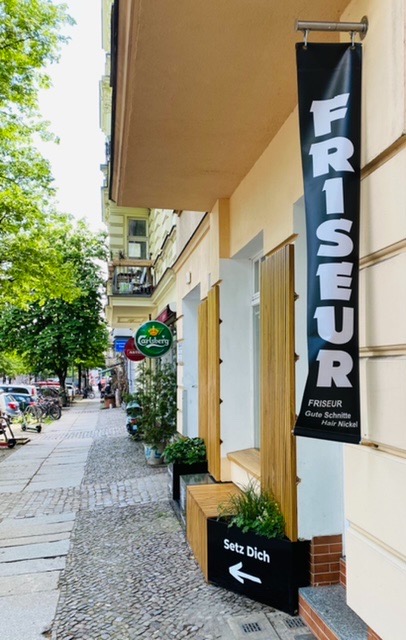
Suche Schrift von »Electric Guitar« aus Tocotronic-Video
Die Schrift ist nicht erhältlich, bitte respektiert unseren Entwurf und baut sie auch nicht nach. Und ich bitte darum, dass falls jemand irgendwie eine Kopie davon haben sollte diese nicht, auch nicht privat, zu verwenden.
Ich bin ein wenig irritiert. Wie kommst du darauf, dass hier jemand eure Schrift nachbauen oder illegal einsetzen könnte?
Und das irgendwo jemand sich in einen Font-Editor einarbeitet, und sich an den Nachbau dieser Schrift heran macht, ohne von deiner Einstellung dazu zu wissen, und diese dann vielleicht auch nur privat nutzt und vielleicht diese dann irgendwann auf eine der Freefont-Seiten auftaucht, wird man auch kaum verhindern können. Wie wissen das jetzt, OK, und es gibt auch noch soo viel, was man machen kann. Wir werden deinen Wunsch also auch respektieren, aber sonstwo?  Zumal die Möglichkeit dagegen vor zu gehen doch eher schwach sind, was jeder Schriftgestalter immer wieder feststellen muss. - siehe auch hier: https://de.wikipedia.org/wiki/Rechtsschutz_von_Schriftzeichen
Zumal der Entwurf ja auf einer vorhandenen Schrift aufbaut und es auch vorher schon sehr ähnliche Schriften gab ...
So sehr ich mich über Dein ursprüngliches Interesse gefreut habe, so sehr wundere ich mich jetzt über Deine Aussage, dass die Schrift ja ohnehin nur eine Variante einer schon vorhandenen sei und doch nicht so besonders. Sind die Trauben jetzt, wo sie sich als nicht greifbar herausgestellt haben, sauer geworden?
Es geht mir bei meiner freundlich formulierten Bitte, den Entwurf zu respektieren nur darum etwaigen Begehrlichkeiten von Leuten, die wie ich "tocotronic schrift" googlen vorzubeugen, und zu bedeuten, dass wir nicht wünschen dass jemand denkt dass wäre ieine anonyme Schrift mit der man herum"forken" könne.
Allgemein hab ich gar nichts gegen Schriftmodifikationen oder Sampling, das kann ja schon eine antimonopolistische Geste der Aneignung sein wenn jemand z.B. das S aus der Disney-Schrift auskoppelt. Und es würde auch einer großen Firma, die seit Jahrzehnten den Schriftentwurf eines vertraglich enteigneten oder längst verstorbenen Designers melkt, nicht weh tun, wenn man mal "ihre" Schrift auf einem Flyer für eine queere Technoparty oder für ein Schulprojekt verwendet.
Hier ist aber es die Hausschrift einer Band, mittlererweile Teil ihrer künstlerischen Identität und ich meine, das ist nicht übertrieben hier zu sagen: freut euch doch über diese kleine Blume in der Landschaft und lasst sie da stehen. 🌺🐛
Deine freundliche Bitte impliziert, dass die User dieses Forums euren Entwurf nicht respektieren und die Schrift sogar nachbauen oder illegal nutzen könnten. Als Einstieg in ein Fachforum finde ich solche Äußerungen schlicht unangebracht. Und es zeugt auch von einer Attitüde, die ich im Kontext der Entstehungsgeschichte nicht ganz nachvollziehen kann.
Hmm, sehe ich nicht so. Eher finde ich dieses Anpampen kein besonders nettes Willkommen. Sowas zum eigenen Werk zu sagen, halte ich für legitim. Da sehe ich keine Anschuldigung drin. Soll man sich hier erst umgucken und das ganze Forum studieren um einschätzen zu können, ob so ein (unschuldiger) Einwurf angebracht ist? Und wenn man sich hier umguckt, sieht man recht viel was nachgezeichnet wird (in der Regel natürlich legal und legitim). Ich verstehe deine Angefasstheit nicht :-?Bzw. könnte man ja auch weniger konfrontativ entgegnen und einfach sagen „Alles klar, das hat keiner vor!“
Muss man sich jetzt bei dir erst vorstellen und etwas Smalltalk betreiben bevor man sagen kann, was einem aufm Herzen liegt :-?
Unverständliche Reaktion! Schon die erste Antwort …
Sorry, netter kann ich nicht. Und Sorry, ich finds generell nicht gut wenn jemand unter Generalverdacht gestellt wird.
Ich kann keinen Generalverdacht erkennen :neenee:
Wenn man aber nach einer Schrift im Typoforum fragt, hat das doch meistens den Grund, dass man ein Interesse hat sie einzusetzen oder etwas ähnliches zu gestalten – zumindest ist das naheliegend, wenn auch hier evtl. nicht der Fall. Und wer weiß, was Pascal schon in dem genannten Toco-Forum oder anderen Fan-Gruppen erlebt hat. Ist aber auch mal wieder müßig … Ich kann deine Reaktion wie gesagt nicht nachvollziehen, für freundlich und nett, sind ja noch genug andere hier :nicken::trost:
ohne dass Urheberschaften hinterfragt worden wären
Muss man ja beim Nachzeichnen in der Regel auch nicht, da nur Schriftnamen bzw. die Schrift-Dateien geschützt sind und nicht die formale Anmutung (sagte nicht mal irgendwer, ein A sei ein A und bleibe ein A?).
Jenseits dessen werden hier doch alle den Wünschen der Schöpfer der Exklusiv-Schrift entsprechen, das läuft hier doch immer sehr kollegial.